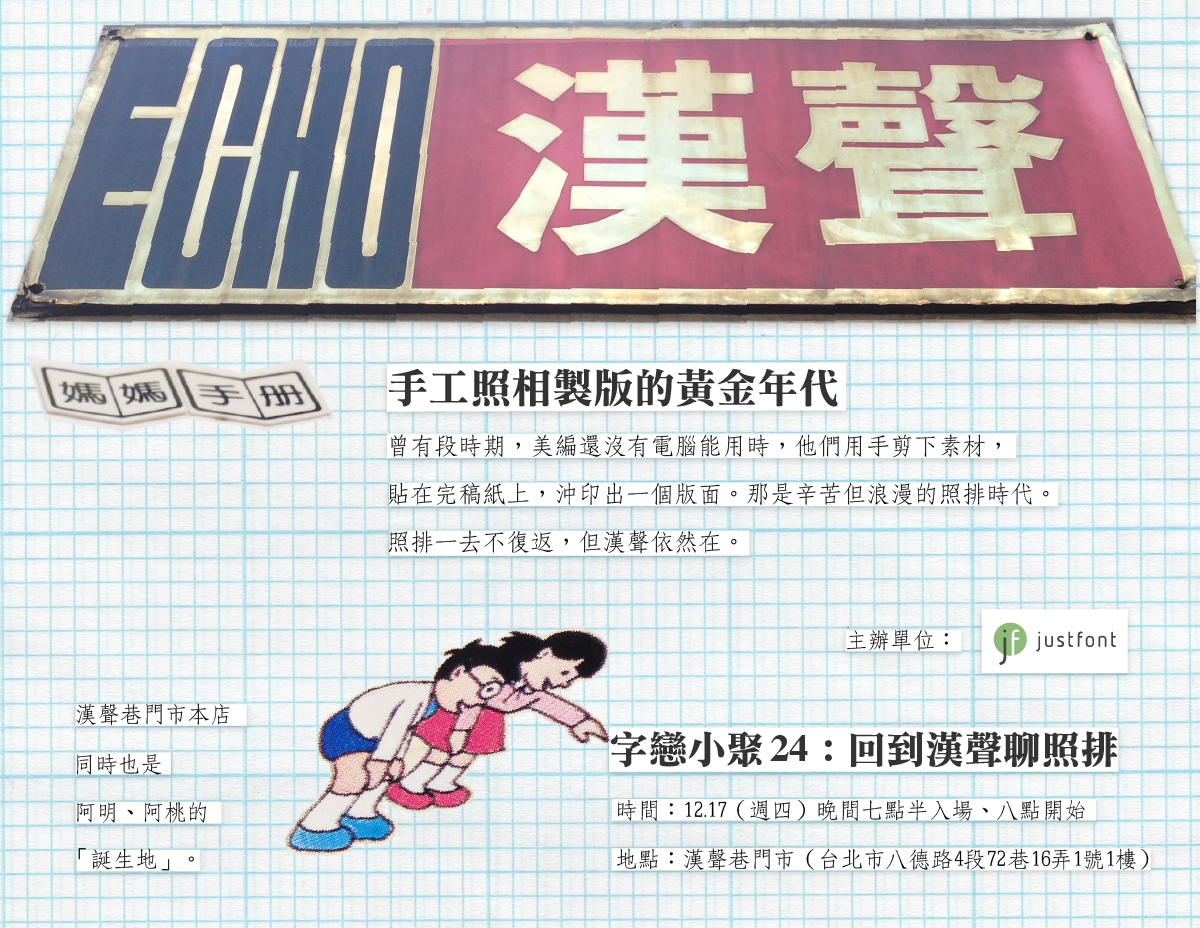
曾經有段時期,美編還沒有電腦能用。他們用手剪下素材,貼在完稿紙上,沖印出一個版面。要調整一個字,必須整段重新剪貼、再拿去沖印。所有的表格都要用尺去瞄、一個 icon 也是先用鉛筆打稿、再用針筆塗黑。如果字型裡面缺字,他們還得自己想辦法剪剪貼貼湊成一個字。要標示漸層、顏色,完全用手寫「留言」所需要的參數值給印刷廠,沒有 colow swatches 可以用。那是辛苦但浪漫的照排時代。照排一去不復返,但漢聲依然在。
就算是這個講究「天下武功,唯快不破」的新媒體時代,漢聲依然保持它的步伐。一本書籍、刊物的製作,至少要花費一年。同時,漢聲也保留了許多照相排版時期的手工完稿,對研究印刷字型歷史的人而言,這是非常珍貴的資料在這天晚上,我們在漢聲巷門市聚會,與漢聲的前輩聊聊照相打字時代的故事。